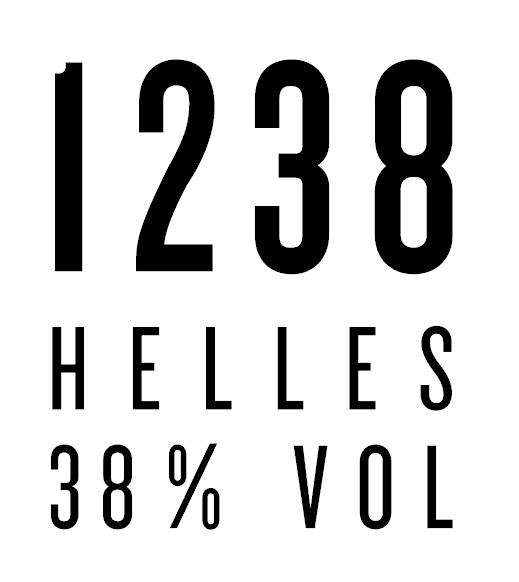
Schrift von einem Liköretikett gesucht.
Weiß jemand um welche Schrift es sich hier handelt. Sehr charakteristisch dabei ist eigentlich nur die Zahl 1.
Hallo Diwarnei, die 1 der Dharma wäre schon SEHR ähnlich, mir ist aber auch auf den zweiten Blick erst aufgefallen, dass die Rundungen bei der Dharma abgeflacht sind. Gut zu erkennen beim großen S und bei der 8. Vielen Dank für die vorgeschlagene Knockout von Hoefler, die passt besser. Gruß, Michael
Ich hätte jetzt eher die Knockout von Hoefler vermutet
Das war auch mein erster Gedanke ...